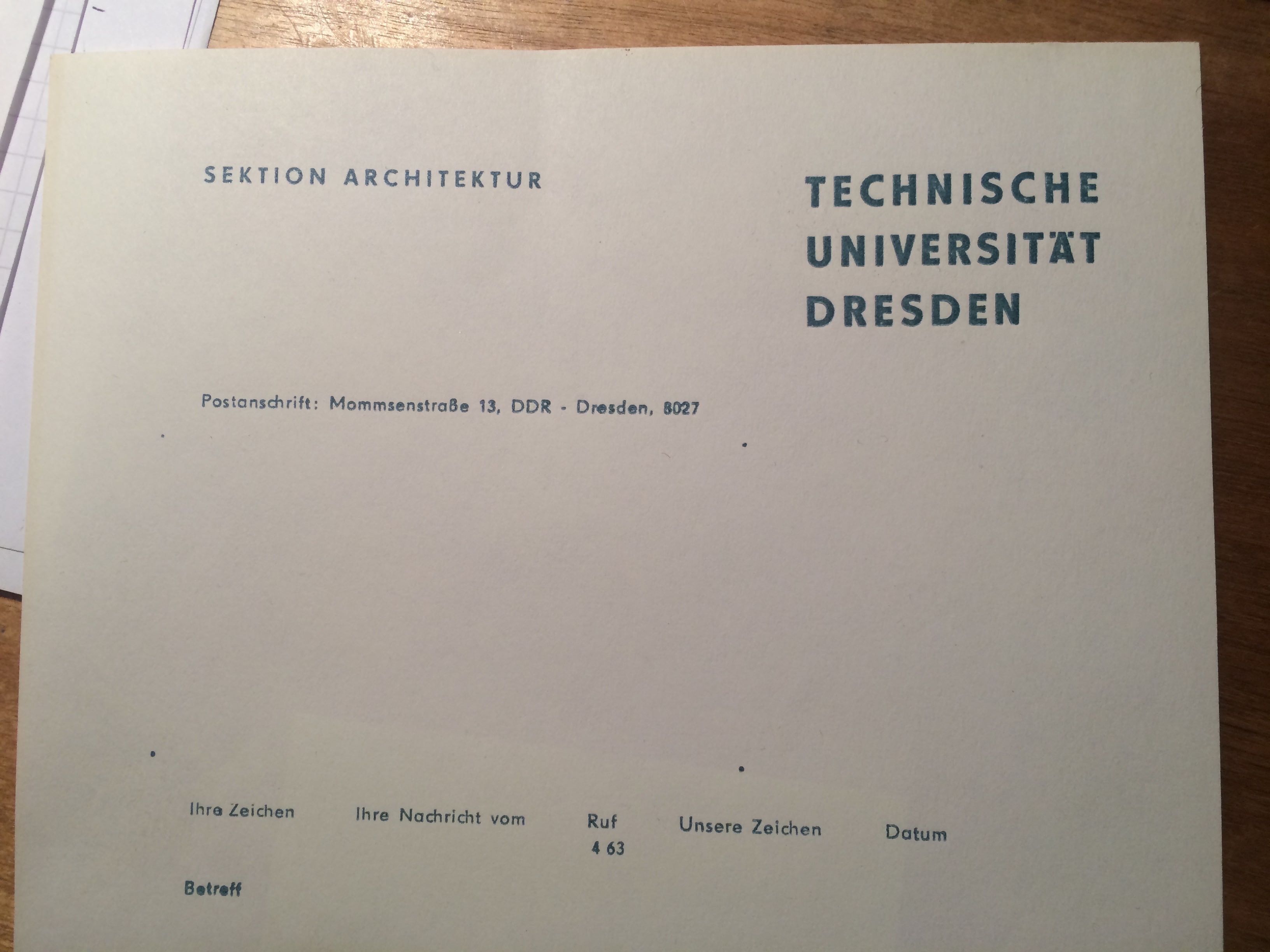
Groteske Frage: Fundamental oder Super?
TU DRESDEN Fundamental, der Rest Super, würde ich sagen. Jedenfalls finde ich spontan keine Zeichen, die dem widersprechen. Das C ist eindeutig kein Super-C, die 7 gehört eindeutig nicht zur Fundamental.